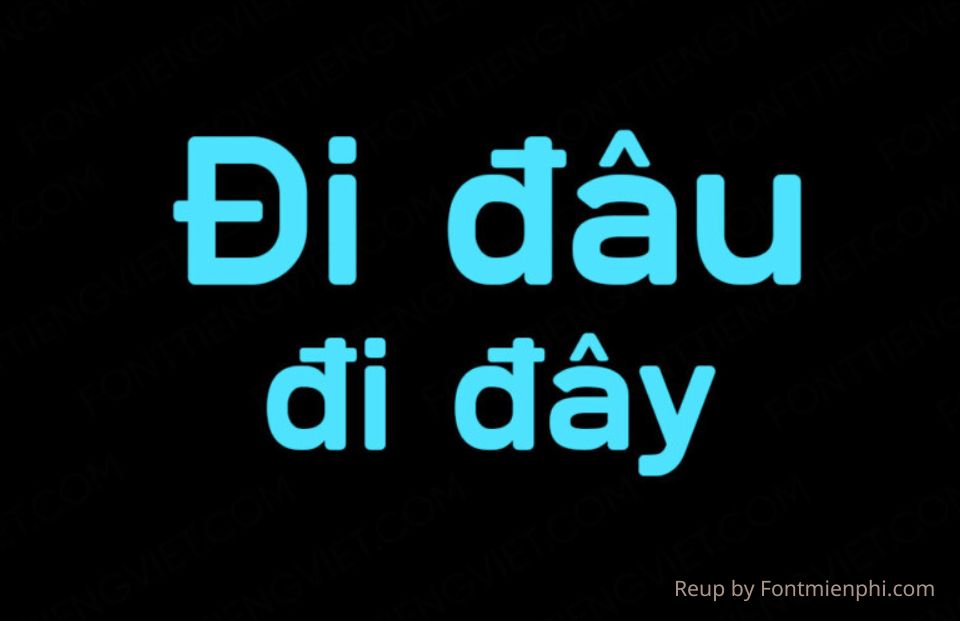
Trong giới thiết kế đồ họa, việc lựa chọn một phông chữ phù hợp quyết định đến 50% sự thành công của một ấn phẩm. Thời gian gần đây, bộ font Việt hóa 1FTV VIP Groste đang làm mưa làm gió trong cộng đồng designer nhờ đường nét tinh tế, hiện đại và khả năng ứng dụng đa dạng.
1. Giới thiệu tổng quan về Font Việt hóa 1FTV VIP Groste
1FTV VIP Groste là một phiên bản phông chữ thuộc họ Grotesque Sans-serif (phông chữ không chân), được đội ngũ 1FTV (1 Font Tiếng Việt) chọn lọc và tiến hành Việt hóa tỉ mỉ.
Lấy cảm hứng từ phong cách thiết kế tối giản nhưng không kém phần sang trọng, bộ font này mang lại cảm giác mạnh mẽ, chắc chắn nhưng vẫn giữ được độ mềm mại cần thiết ở các nét bo góc. Việc Việt hóa chuẩn xác giúp các dấu câu tiếng Việt (huyền, sắc, hỏi, ngã, nặng) được tinh chỉnh hài hòa, không bị lỗi hiển thị hay lệch khoảng cách (kerning) khi gõ.
Đặc điểm nổi bật của 1FTV VIP Groste
• Thiết kế Sans-serif hiện đại: Đường nét sạch sẽ, gọn gàng, mang đậm hơi thở của nghệ thuật typography đương đại.
• Hỗ trợ tiếng Việt 100%: Dấu câu được thiết kế lại hoàn toàn để phù hợp với đặc thù của bảng chữ cái tiếng Việt, đảm bảo tính thẩm mỹ cao nhất.
• Đa dạng độ đậm nhạt (Weights): Cung cấp nhiều định dạng từ Thin, Regular cho đến Bold, Black, giúp designer linh hoạt trong việc phân cấp thông tin.
• Khả năng đọc tốt (Legibility): Hoạt động hoàn hảo ở cả kích thước lớn (tiêu đề) và kích thước nhỏ (văn bản nội dung).
2. Ứng dụng của Font 1FTV VIP Groste trong thiết kế
Với tính linh hoạt cao, font 1FTV VIP Groste Việt hóa có thể được ứng dụng trong hầu hết các lĩnh vực thiết kế đồ họa hiện nay:
Thiết kế nhận diện thương hiệu (Branding)
Sự mạnh mẽ và chuyên nghiệp của VIP Groste biến nó trở thành ứng cử viên sáng giá cho việc thiết kế Logo, hệ thống văn bản thương hiệu, namecard hay bao bì sản phẩm. Phông chữ này đặc biệt phù hợp với các thương hiệu về công nghệ, thời trang, kiến trúc hoặc nội thất.
Thiết kế Giao diện người dùng (UI/UX)
Nhờ vào tính dễ đọc trên màn hình điện tử, 1FTV VIP Groste rất được ưa chuộng khi làm phông chữ chính cho Website hoặc Mobile App. Nó giúp mang lại trải nghiệm người dùng mượt mà và giao diện trông cực kỳ “sạch” (clean).
Ấn phẩm Truyền thông & Mạng xã hội
Dùng font này để làm Typography cho các banner quảng cáo, bài đăng Facebook, Instagram, hay Poster sự kiện sẽ giúp thông điệp của bạn trở nên nổi bật và thu hút ánh nhìn ngay lập tức.
• Kết hợp font (Font Pairing): Để thiết kế thêm phần ấn tượng, bạn có thể kết hợp 1FTV VIP Groste (dùng làm tiêu đề) với một phông chữ Serif (có chân) truyền thống cho phần nội dung (body text), tạo ra sự tương phản thú vị.